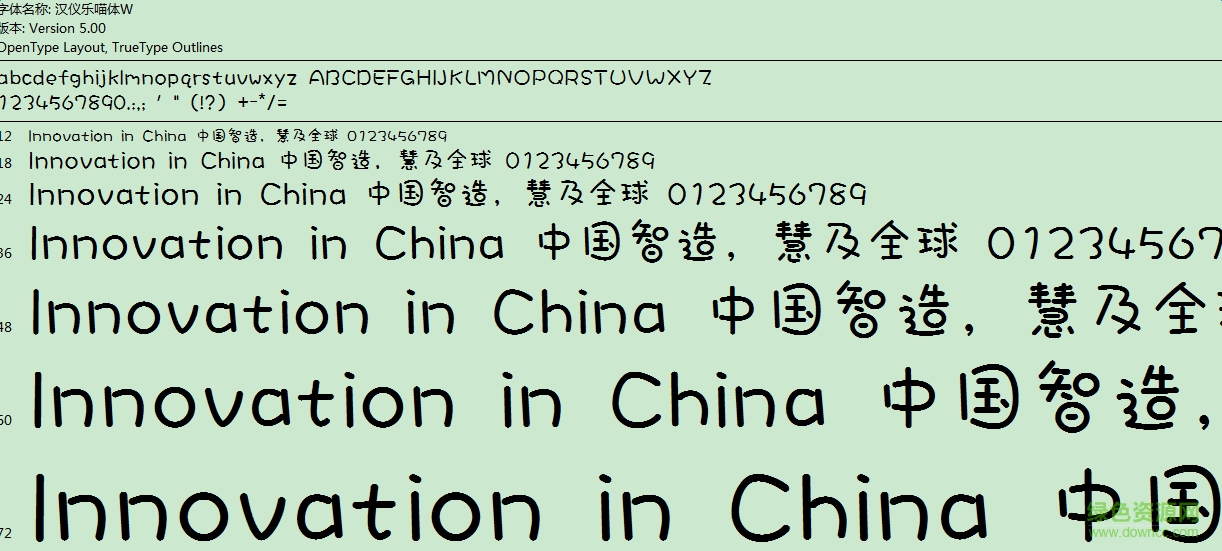
漢儀樂(lè)喵體w是漢儀系列可愛(ài)風(fēng)格字體軟件,該字體透露著兒童悠閑自在的氣息,筆畫(huà)呆萌隨意,非常的養(yǎng)眼,歡迎大家來(lái)綠色資源網(wǎng)踴躍下載哦!
漢儀樂(lè)喵體w是一款非常好玩的藝術(shù)字體,融合了很多可愛(ài)的元素,非常適合藝術(shù)類朋友們使用。